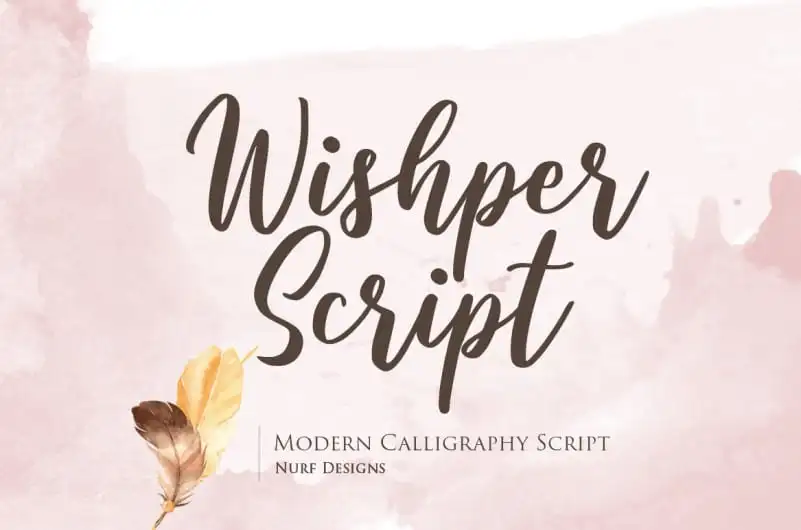
Wishper Script Font – Download Grátis
Wishper Script é uma elegante fuente escrita a mão com um toque casual e amigável. Suas linhas suaves e delicadas tornam esta fonte perfeita para qualquer projeto criativo, seja você buscando fontes para Instagram ou scripts de calligrafia para DIY projetos. Este estilo handwritten vai transformar cada conceito original em verdadeiras obras de arte. Em sua categoria de Calligraphy Fonts, a fonte de designer nurfdesigns oferece um toque único e versátil que será uma ótima escolha para qualquer projeto visual interessante. Não importa qual seja seu próximo projeto, Wishper Script pode ser a solução perfeita para dar vida à sua ideia, transformando-a em algo verdadeiramente especial.